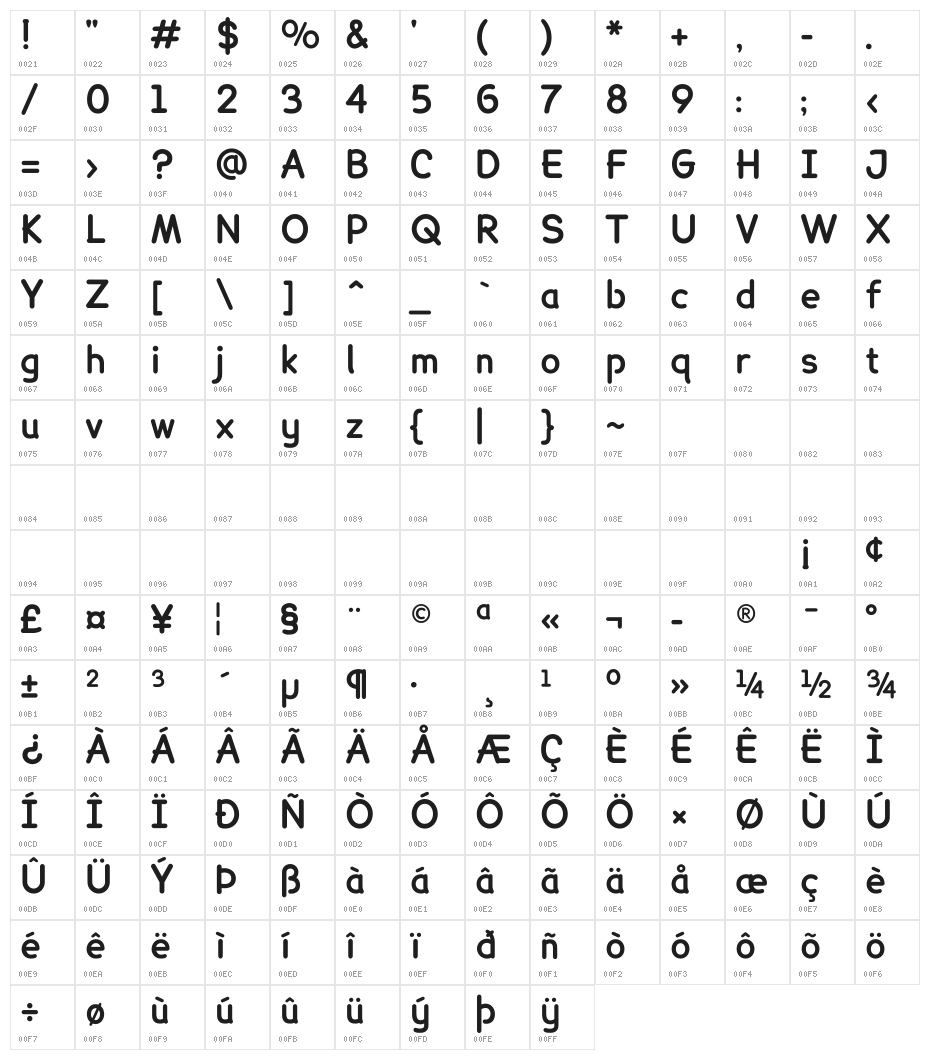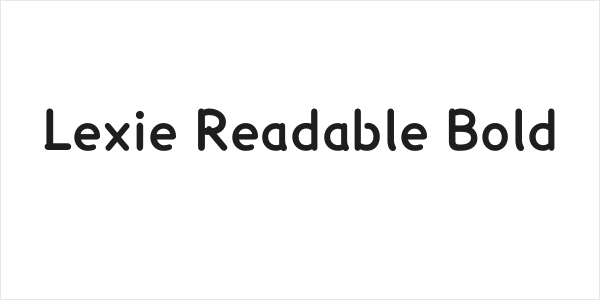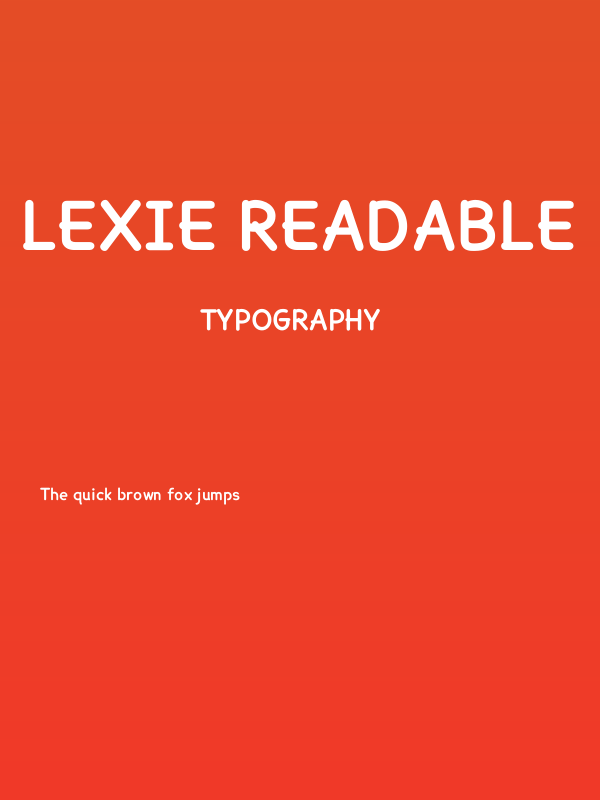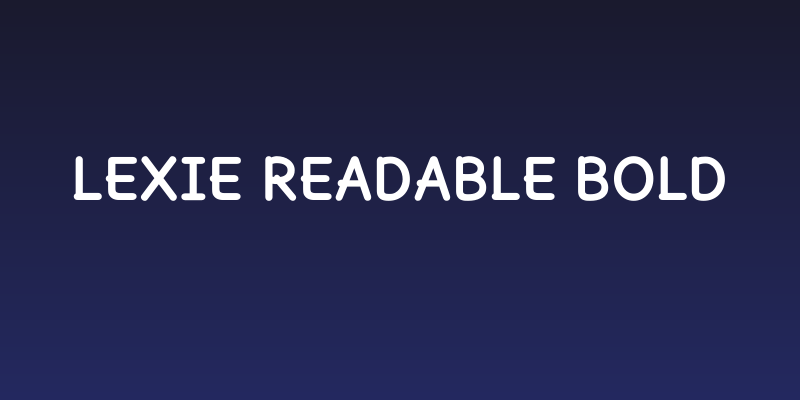
Lexie Readable Bold Font
| Name | Lexie Readable Bold |
| Gewicht | Bold |
| Kategorien | Sans Serif |
| Anwendungsfall | Headlines, Body text, Logos |
| Vorgeschlagene Projekte | Ideal for educational materials, children's books, user interfaces, signage, and branding projects that require a clear and approachable typeface. |